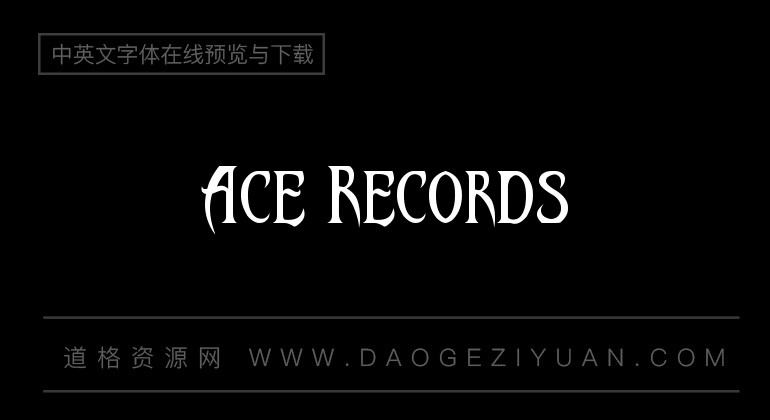
Ace Records 是一种字体,它的特点是简洁、现代和通用。这种字体通常用于设计海报、广告、标志和其他类型的印刷品。 Ace Records 字体由 Alex Banks 设计,其设计灵感源于现代音乐和电影行业。这种字体的特点是它的精简性和细节,它的字母形状非常流畅,因此易于阅读和识别。这种字体还具有广泛的应用性,可以用于许多不同的设计项目中,因此备受设计师的青睐。内容介绍
Ace Records是一款非常不错的手写艺术字体,具有很好的视觉感,适合于文化类的宣传设计、商业类品牌的广告和产品包装设计以及个性化文字排版等较多场景。